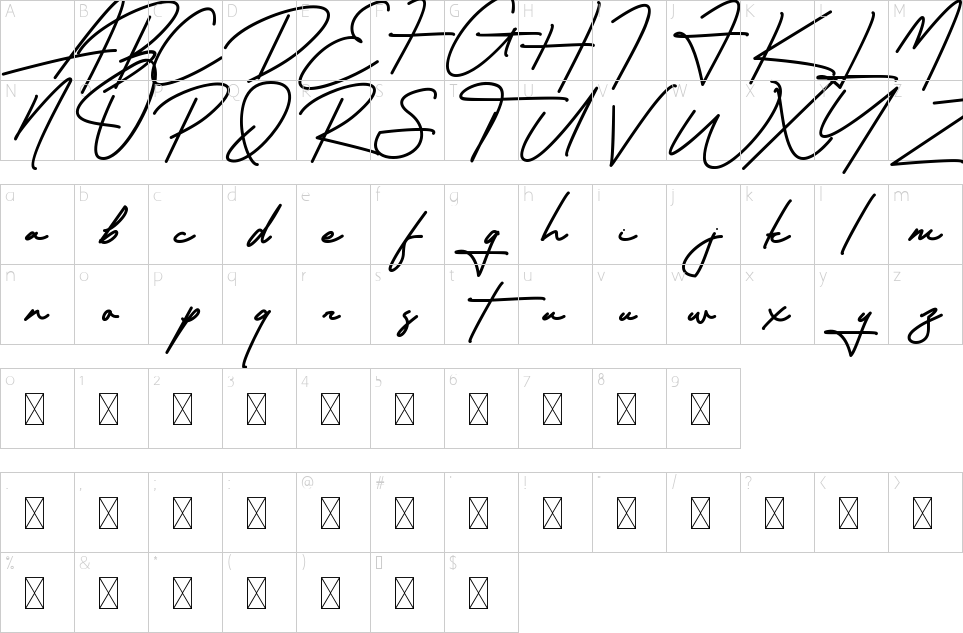
Almonde Handwritten Font – Download Grátis
A Almonde Handwritten é uma fonte única e encantadora que transmite uma atmosfera envolvente e natural, certamente propícia para um uso em páginas de design gráfico em alta projeção. Desenvolvida por Muwatta, esta fonte foi projetada para oferecer um tom suave e harmonioso, perfeito para textos de design, anúncios e design gráfico. Com uma característica doce e aconchegante, a Almonde Handwritten é uma escolha perfeita para tornar seus projetos ainda mais únicos e apaixonantes. Até agora, mais de 1.237 pessoas já desfrutaram da possibilidade de adquirir esta fonte gratuita, demonstrando a sua popularidade entre os criadores de design. Se você está em busca de uma fonte que se destaca da lotação, a Almonde Handwritten é uma excelente escolha para se juntar ao seu catálogo.